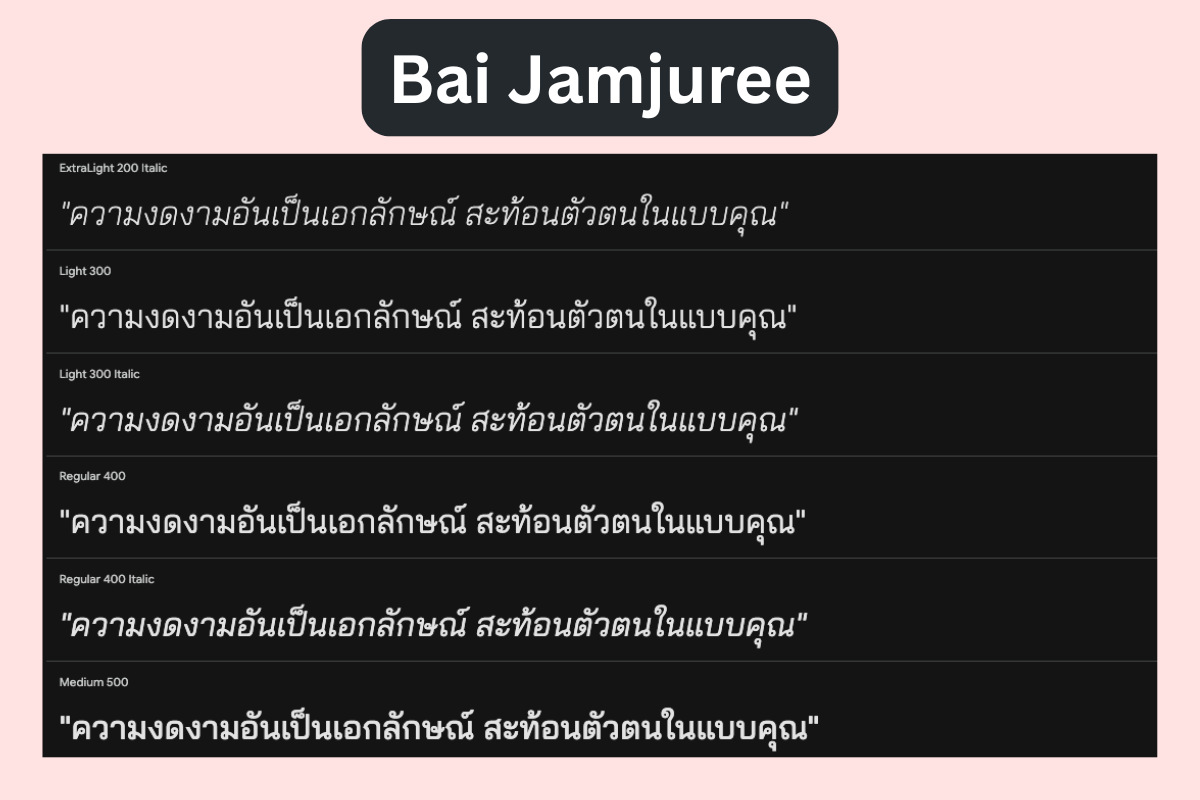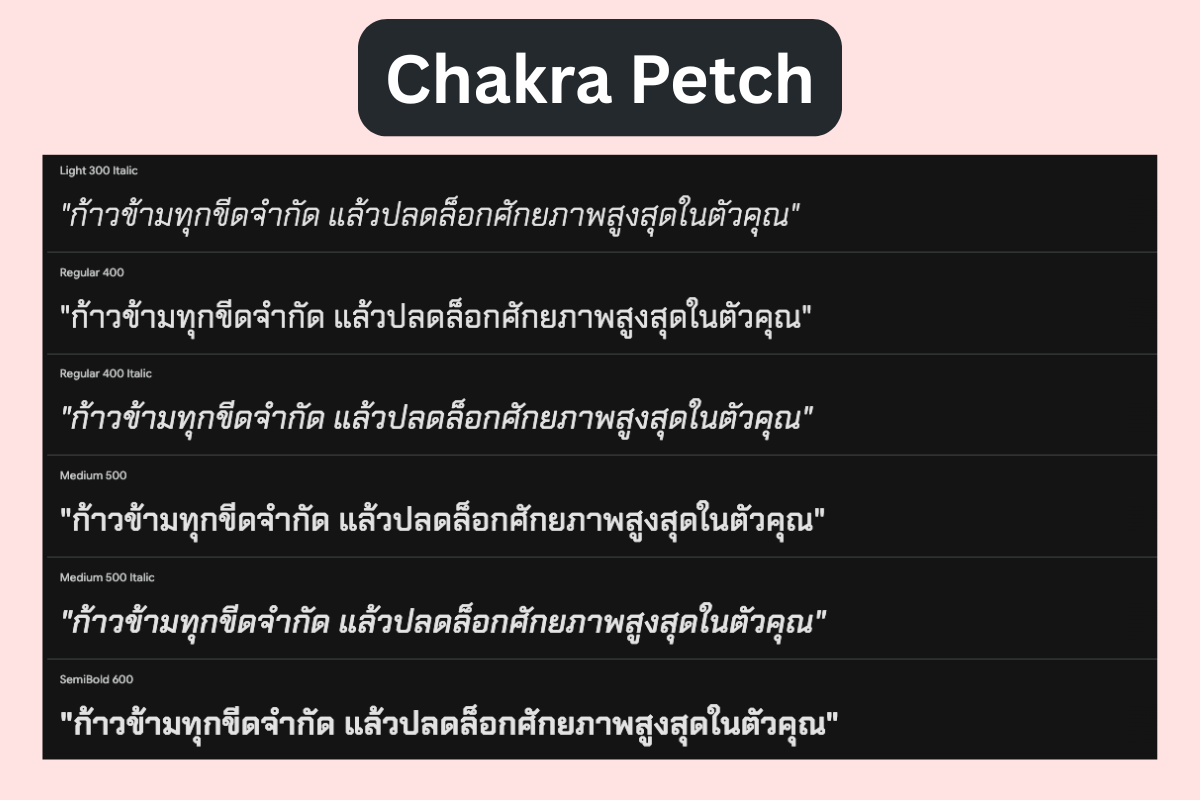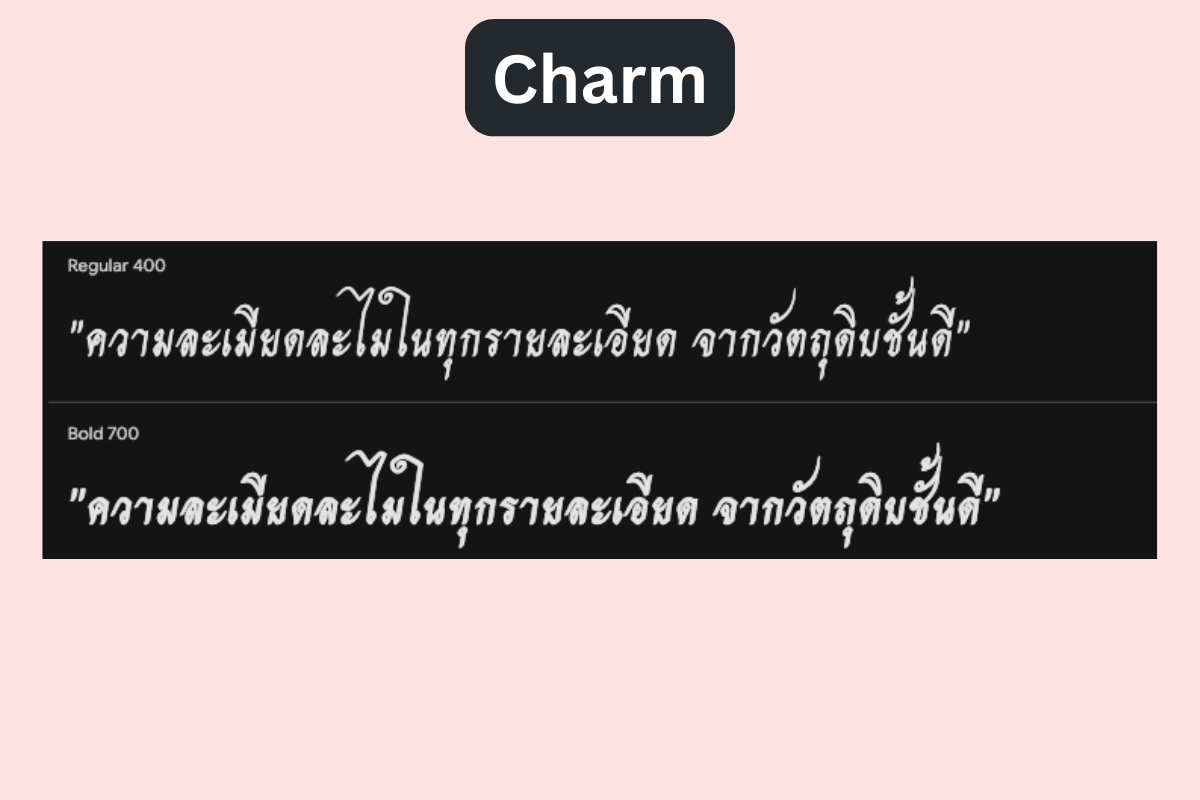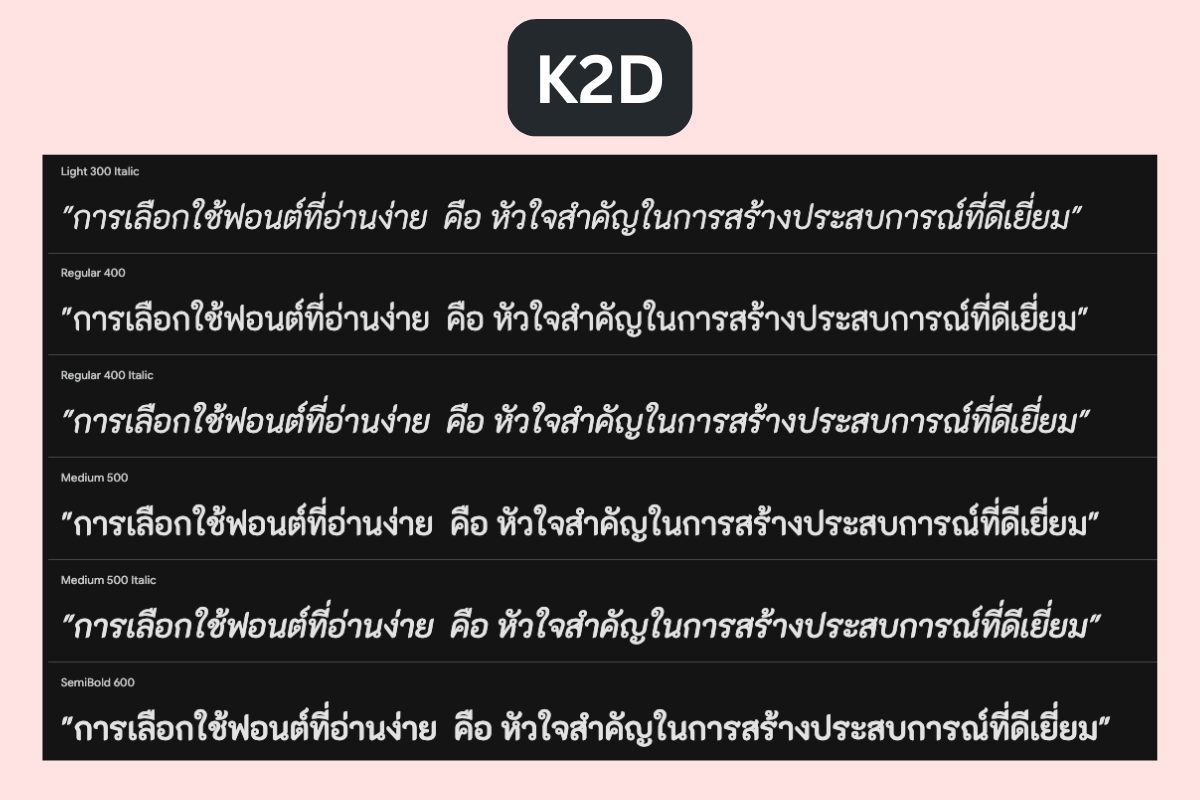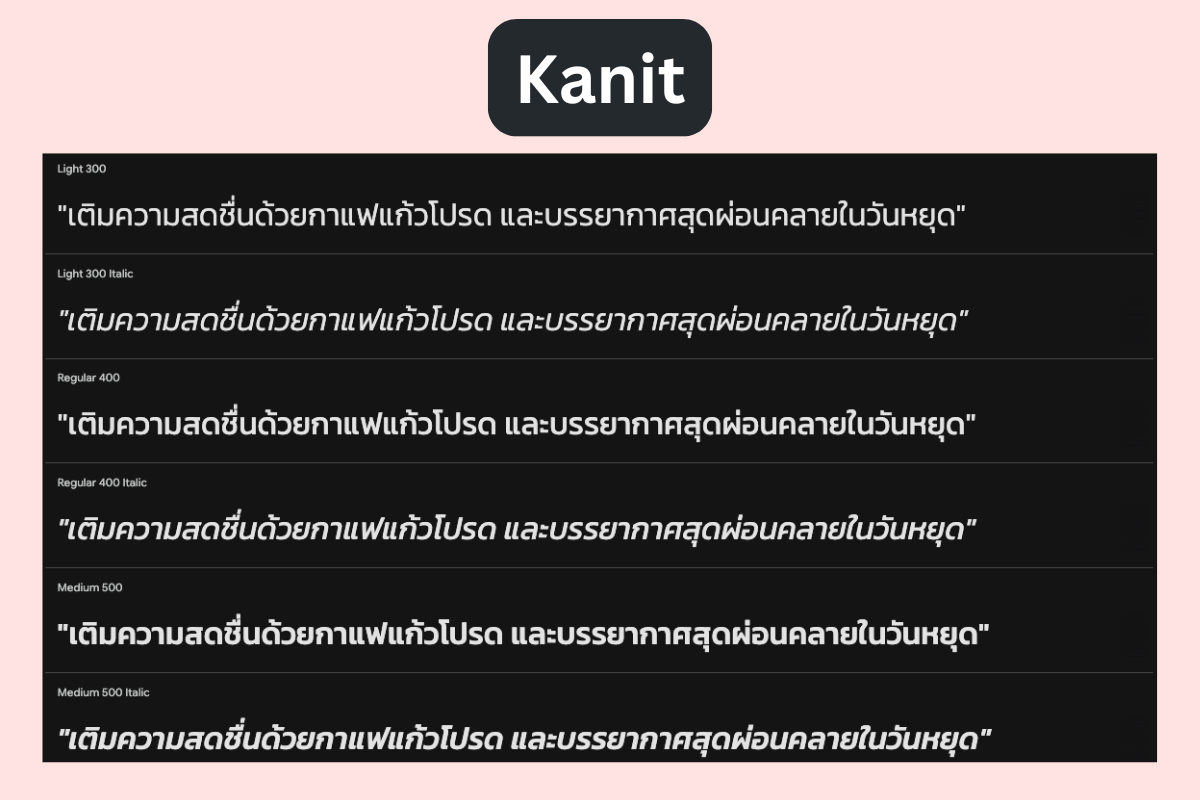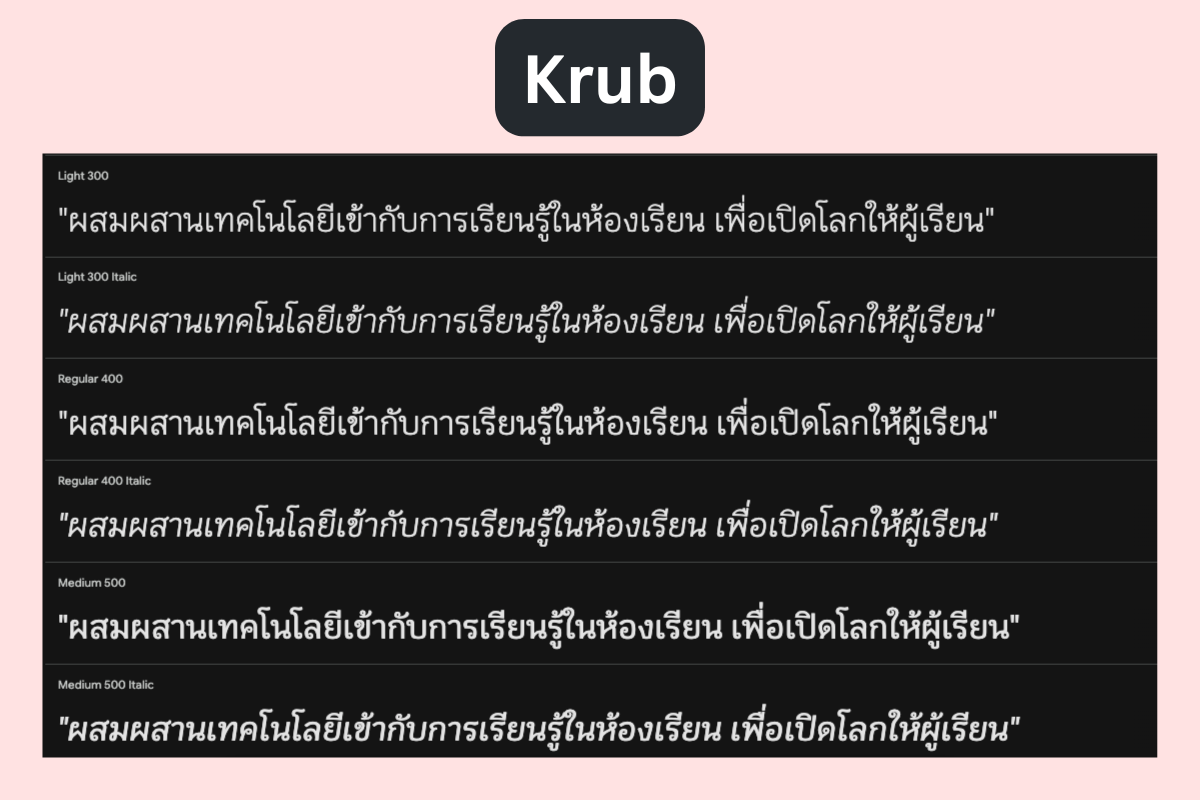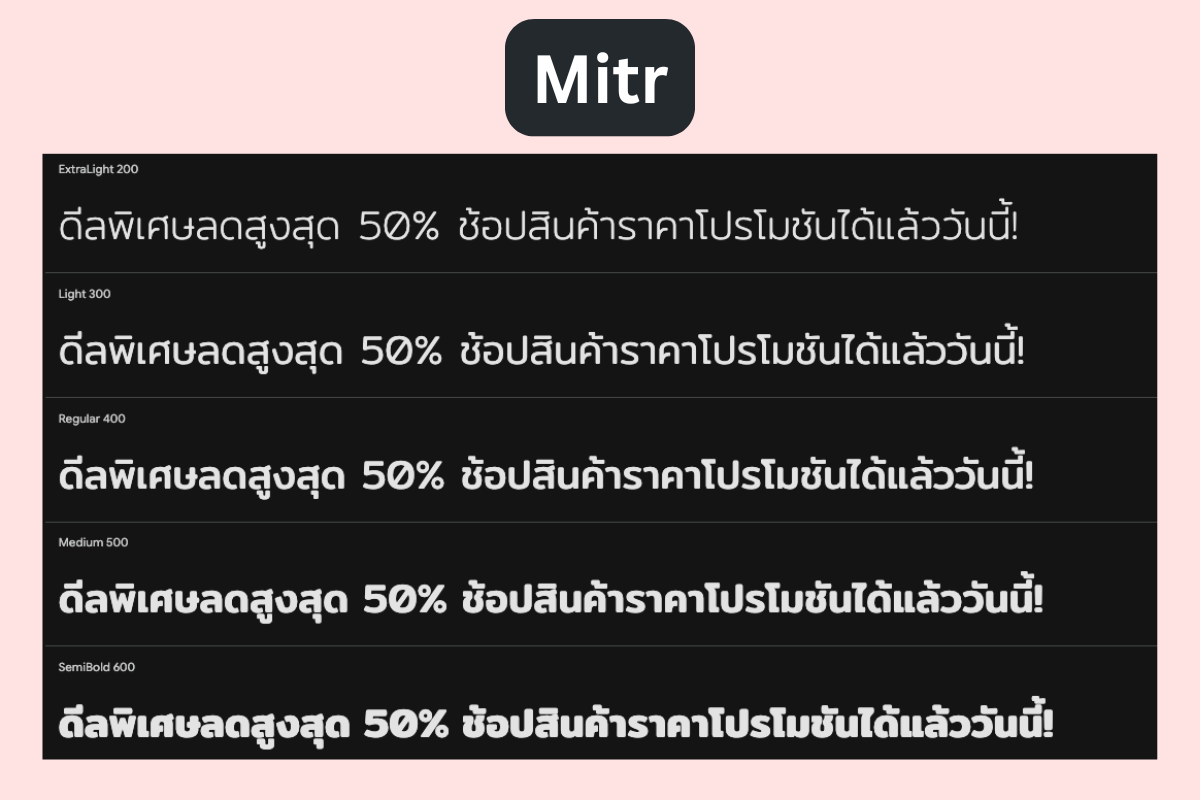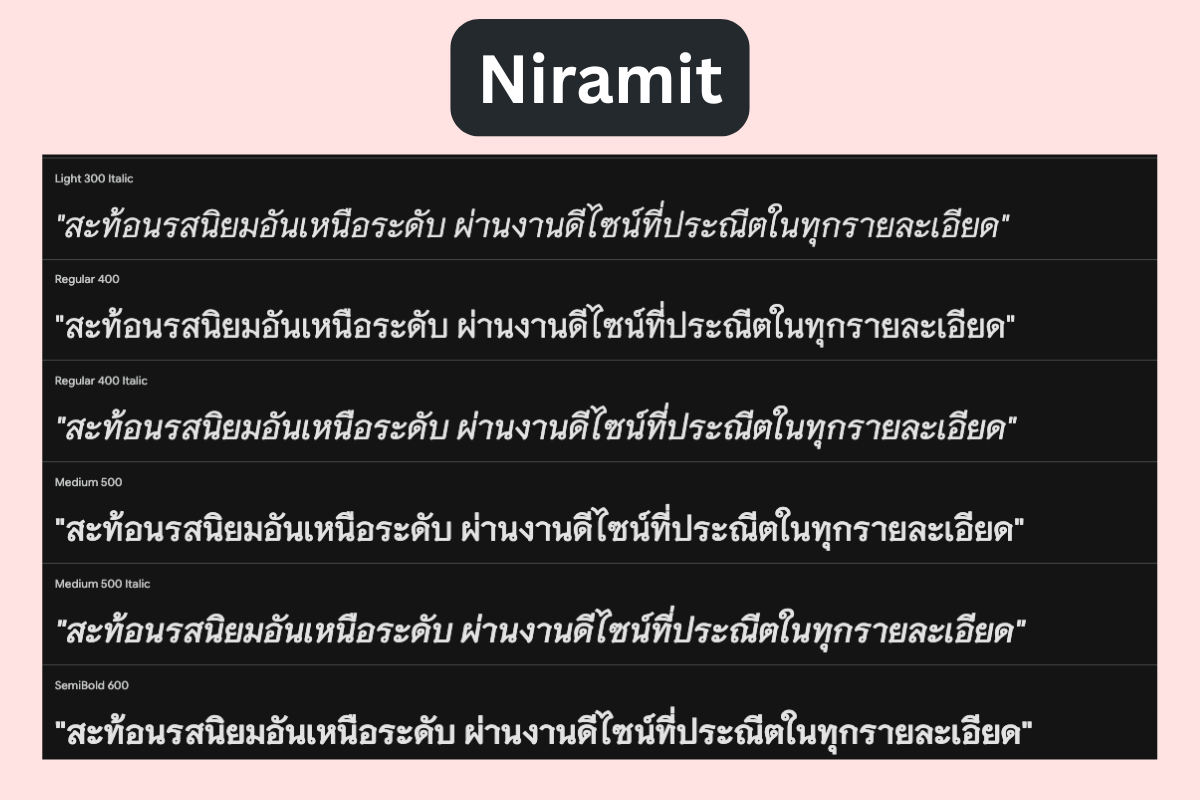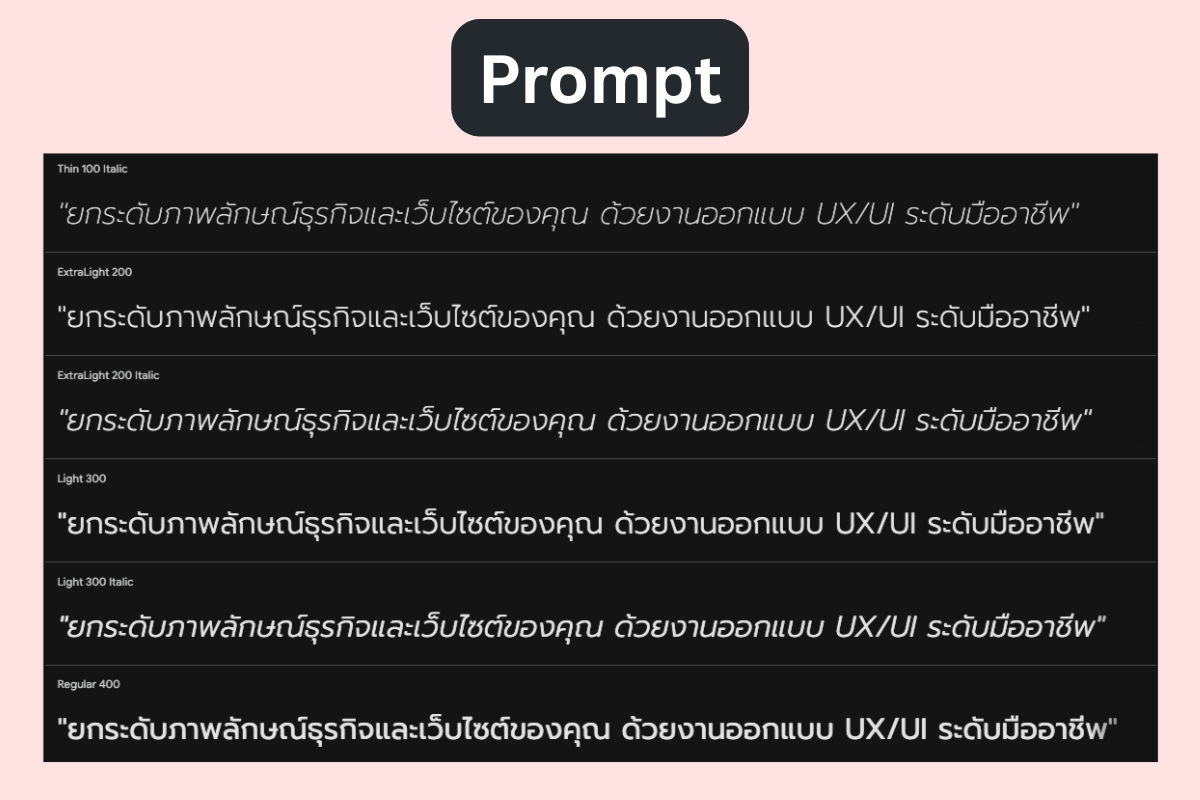
10 Thai Fonts ฟรีที่แนะนำ
ปี 2026
1. Prompt (พร้อมท์)
ฟอนต์ไทยสไตล์โมเดิร์นยอดฮิตอันดับต้น ๆ ของวงการดีไซน์ โครงสร้างอักษรมีความเป็นสากล โปร่งกว้าง และสะอาดตา
ช่วยเพิ่มภาพลักษณ์ความทันสมัย และสร้างความเป็นมืออาชีพให้กับแบรนด์ได้อย่างสมบูรณ์แบบ
• สไตล์: Sans-serif (ไม่มีหัว) | น้ำหนัก: 9 ตัว
(Thin ถึง Black)
• เหมาะกับอะไร: หัวข้อเว็บไซต์ (H1/H2), งาน UI Design,
โพสต์โซเชียลมีเดีย ที่ต้องการลุคโมเดิร์น
และเป็นทางการในเวลาเดียวกัน
• ไม่เหมาะกับอะไร: ย่อหน้าเนื้อหายาว ๆ ที่มีขนาดตัวอักษรเล็กมาก เพราะอาจอ่านยากกว่าฟอนต์มีหัว
2. Sarabun (สารบัญ)
ฟอนต์มาตรฐานระดับประเทศ ที่ออกแบบมาเพื่อการอ่านเนื้อหาปริมาณมากโดยเฉพาะ มีโครงสร้างตัวอักษรแบบมีหัวที่ชัดเจน
เป็นระเบียบ เรียบง่าย และสบายตา ทำให้เป็นตัวเลือกหลักสำหรับงานที่เน้นความน่าเชื่อถือ
• สไตล์: Serif (มีหัวแบบมาตรฐาน) | น้ำหนัก: 8 ตัว
(Thin ถึง Bold)
• เหมาะกับอะไร: ย่อหน้าเนื้อหาบทความ (Body Text), เอกสารทางการขององค์กร,
เว็บไซต์ข่าว และรายงานประจำปี
• ไม่เหมาะกับอะไร: งานที่ต้องการความโฉบเฉี่ยว
ทันสมัยมาก ๆ หรือแบรนด์สายวัยรุ่น
3. Kanit (คณิต)
ฟอนต์ไม่มีหัวที่มีจุดเด่นด้านความทรงพลังและความกว้าง
ของสัดส่วนตัวหนังสือ ให้ความรู้สึกโฉบเฉี่ยว ตื่นตัว และดึงดูดสายตาได้ทันที
จึงมักถูกนำไปใช้ในงานที่ต้องการสร้างความสะดุดตาเป็นพิเศษ
• สไตล์: Sans-serif (ไม่มีหัว โครงสร้างกว้าง ลุคสปอร์ต) | น้ำหนัก: 9 ตัว
• เหมาะกับอะไร: ป้ายโปรโมชัน, ข้อความพาดหัว
ที่เน้นความโดดเด่นสะดุดตา, แบรนด์สายฟิตเนส หรือสินค้าไอที
• ไม่เหมาะกับอะไร: การนำไปใช้เป็นตัวหนังสืออ่านยาวๆ
หลายพารากราฟ
4. K2D (เคทูดี)
ฟอนต์แนวโมเดิร์น Sans-serif ที่ผสมผสานความโค้งมน
เข้ากับเส้นสายที่สะอาดตา ให้ภาพลักษณ์ที่เป็นมิตร
เข้าถึงง่าย แต่ยังคงความเรียบร้อย มักถูกเลือกใช้ในธุรกิจยุคใหม่
ที่ต้องการสร้างบรรยากาศผ่อนคลาย และทันสมัย
• สไตล์: Sans-serif (ไม่มีหัว สไตล์โมเดิร์นโค้งมน) |
น้ำหนัก: 6 ตัว
• เหมาะกับอะไร: เว็บไซต์เทคโนโลยี, สตาร์ตอัป,
หน้าขายสินค้า (Landing Page),
โพสต์โฆษณาบนโซเชียลมีเดียที่ต้องการความรู้สึกเป็นมิตร
• ไม่เหมาะกับอะไร: งานเอกสารทางการมากๆ
เช่น สัญญากฎหมาย หรือหนังสือราชการ
5. Chakra Petch (จักรเพชร)
ฟอนต์ทรงเหลี่ยมที่มีเอกลักษณ์โดดเด่นสไตล์เทคโนโลยี โครงสร้างตัวอักษรเน้นมุมตัดและเส้นตรงที่แข็งแกร่ง
ให้ความรู้สึกเหมือนโลกอนาคต เครื่องจักร นวัตกรรม และไซเบอร์ได้อย่างชัดเจน
• สไตล์: Square Sans-serif (ไม่มีหัว ทรงเหลี่ยมเทคโนโลยี) | น้ำหนัก: 5 ตัว
• License: SIL Open Font License 1.1
• เหมาะกับอะไร: เว็บไซต์เกม, ธุรกิจยานยนต์, นวัตกรรม AI, งานออกแบบสไตล์ไซเบอร์พังก์
• ไม่เหมาะกับอะไร: ธุรกิจบริการสุขภาพ, แบรนด์เด็ก
หรือสินค้าสปา
6. Niramit (นิรมิต)
ฟอนต์แบบมีหัวที่มีกลิ่นอายความเป็นไทยอย่างชัดเจน
เส้นสายมีความงดงาม โปร่งกว้าง เรียบร้อย และคลาสสิก
ให้ความรู้สึกสงบนิ่ง น่าเชื่อถือ และสะท้อนภาพลักษณ์
ความสง่างามแบบไทยได้อย่างลงตัว
• สไตล์: Modern Serif (มีหัวสไตล์โมเดิร์น) |
น้ำหนัก: 6 ตัว
• License: SIL Open Font License 1.1
• เหมาะกับอะไร: หนังสือ, นิตยสารเชิงวัฒนธรรม,
สื่อประชาสัมพันธ์องค์กรไทย,
บรรจุภัณฑ์สินค้าไทยพรีเมียม หรือสถาบันการศึกษา
• ไม่เหมาะกับอะไร: สื่อสายเทคโนโลยี, สตาร์ตอัป, สื่อวัยรุ่น
หรือเว็บไซต์ที่ต้องการความฉูดฉาด
7. Mitr (มิตร)
ฟอนต์กึ่งมีหัวที่ออกแบบมาให้อ่านง่าย สบายตา
และดูเป็นมิตรตามชื่อ มีความสมดุลระหว่างความทันสมัย
กับโครงสร้างแบบดั้งเดิม ทำให้เข้าถึงคนได้ทุกกลุ่มวัย
โดยไม่ดูเป็นทางการจนเกินไป
• สไตล์: Semi-sans-serif (มีหัวมินิมอล) | น้ำหนัก: 6 ตัว
• License: SIL Open Font License 1.1
• เหมาะกับอะไร: แอปพลิเคชันการศึกษา, เว็บไซต์สถาบันติวเตอร์, เนื้อหาอินโฟกราฟิก
• ไม่เหมาะกับอะไร: แบรนด์ที่ต้องการภาพลักษณ์ดุดัน
หรือหรูหราระดับไฮเอนด์
• ดาวน์โหลดทางการ: Google Fonts – Mitr
8. Krub (ครับ)
ฟอนต์ Display สไตล์ไทยร่วมสมัยที่มีเอกลักษณ์เฉพาะตัวสูงมาก ด้วยดีไซน์หัวอักษรแบบม้วนขมวด
และเส้นสายคดเคี้ยวสลับซับซ้อน มอบอารมณ์ศิลป์
และความโดดเด่นที่ไม่ซ้ำใครให้กับงานดีไซน์
Thai-Fonts-Krub
• สไตล์: Serif / Display (หัวม้วนขมวด มีเอกลักษณ์เฉพาะตัวสูง) | น้ำหนัก: 6 ตัว
• License: SIL Open Font License 1.1
• เหมาะกับอะไร: งานออกแบบพาดหัวสั้นๆ (Headline),
งานการ์ดอวยพร, ป้ายร้าน, โลโก้
หรือสื่อที่ต้องการลุคแบบงานคราฟต์/อาร์ต
• ไม่เหมาะกับอะไร: ตัวหนังสืออ่านยาวๆ (Body Text),
งานเอกสารทางการ, งาน UI
หรือหน้าเว็บที่ต้องการความคลีน สบายตา
• ดาวน์โหลดทางการ: Google Fonts – Krub
9. Charm (ชาร์ม)
ฟอนต์สไตล์ Script ลายมือหวัดตัวเขียนอ่อนช้อย พริ้วไหวสวยงาม ถ่ายทอดความรู้สึกอ่อนโยน ละมุนละไม และโรแมนติก
ช่วยเติมเสน่ห์ และความพรีเมียมสไตล์งานทำมือให้กับชิ้นงาน
Thai-Fonts-Chram
• สไตล์: Script (ลายมือหวัดอ่อนช้อย) | น้ำหนัก: 2 ตัว
• License: SIL Open Font License 1.1
• เหมาะกับอะไร: การ์ดอวยพร, โลโก้ร้านขนม,
บรรจุภัณฑ์สินค้าออร์แกนิก
• ไม่เหมาะกับอะไร: การนำไปใช้เป็นฟอนต์หลักของเว็บไซต์ หรือเนื้อหาย่อย
• ดาวน์โหลดทางการ: Google Fonts – Charm
10. Bai Jamjuree (ไทรจามจุรี)
ฟอนต์กึ่งทรงเหลี่ยมมีหัวที่ถูกพัฒนามาเพื่อเน้นการจัดเรียงข้อมูลที่มีความซับซ้อนให้ดูเป็นระเบียบ อ่านง่ายสบายตา
ให้ลุคที่เป็นระบบ มีโครงสร้างชัดเจน และทรงพลัง
Thai-Fonts-Bai-Jamjuree
• สไตล์: Semi-serif (ทรงกึ่งเหลี่ยมมีหัว) | น้ำหนัก: 6 ตัว
• License: SIL Open Font License 1.1
• เหมาะกับอะไร: หน้าแสดงผลตารางข้อมูล, ระบบบริหารจัดการหลังบ้าน (ERP/CRM), แอปการเงิน
• ไม่เหมาะกับอะไร: งานสื่อสิ่งพิมพ์การ์ดแต่งงาน
หรือสินค้าแนววินเทจ
• ดาวน์โหลดทางการ: Google Fonts – Bai Jamjuree
License ของ Thai Fonts ฟรี: OFL, Apache 2.0 และ Free for Personal Use ต่างกันอย่างไร?
ปัญหาส่วนใหญ่ที่ทำให้ธุรกิจถูกฟ้องร้องเรื่องลิขสิทธิ์ฟอนต์
มาจากความเข้าใจผิด ว่า
“ดาวน์โหลดฟรี = นำไปใช้ทำอะไรก็ได้”
ซึ่งในความเป็นจริง สัญญาอนุญาตแบ่งออกเป็น 3 ประเภทหลัก ๆ :
SIL Open Font License (OFL)
เป็น License ยอดนิยมบน Google Fonts ที่เสรีที่สุด
เพราะเจ้าของฟอนต์หลาย ๆ เจ้า อนุญาตให้คุณนำฟอนต์ไทยไป
ทั้งใช้ในงานส่วนตัว และงานเชิงพาณิชย์ (Commercial Use)
ได้ฟรีแบบ 100% ทั้งบนสิ่งพิมพ์ เว็บไซต์ แอปพลิเคชัน
หรือสื่อโฆษณา รวมถึงสามารถนำไปฝัง (Embed) ในโค้ดเว็บได้
โดยไม่ต้องเสียค่าใช้จ่าย
Apache License 2.0
มีความคล้ายคลึงกับ OFL พอสมควร
เนื่องจากเปิดให้ใช้นำไปประกอบธุรกิจได้ฟรี
แต่ฟอนต์บางประเภทก็จะมีข้อกำหนดเพิ่มเติม
ในฝั่งนักพัฒนาซอฟต์แวร์ เช่น หากมีการแก้ไขตัวโค้ดฟอนต์
เพื่อแจกจ่ายต่อ ต้องมีการแนบเอกสารแจ้งสิทธิ์
และเครดิตของต้นฉบับไว้ในระบบด้วย
Thai Fonts ที่ฟรีเฉพาะงานส่วนตัว — วิธีเช็กก่อนใช้ในงานลูกค้า
ฟอนต์ตามเว็บแจกฟอนต์ทั่วไปจำนวนมาก มีการระบุเงื่อนนไขการใช้งานว่าเป็นฟอนต์สำหรับ Personal Use Only
แปลว่าคุณสามารถใช้ทำการบ้านทำพอร์ตโฟลิโอส่งครู
หรือทำคอนเทนต์ที่ไม่ได้ถูกนำไปยิงโฆษณาได้ฟรี
แต่ห้ามนำไปใช้กับงานที่มีการจ้างวาน เช่น ทำเพจร้านค้า
ทำแบนเนอร์สินค้าให้ลูกค้า หรือแปะบนหน้าเว็บขายของ
เพราะถ้าหากนำไปใช้ จะถือว่าละเมิดลิขสิทธิ์ทันที
Checklist 4 ข้อ ก่อนใช้ Thai Fonts ฟรีในงานเชิงพาณิชย์
1. อ่านไฟล์ Readme / License.txt ที่ติดมากับโฟลเดอร์ Zip เสมอ
2. จับภาพหน้าจอ (Screenshot) หน้าเว็บที่ดาวน์โหลด
ซึ่งระบุข้อความ “Free for Commercial Use”
เก็บไว้เป็นหลักฐาน
3. ตรวจสอบว่าเป็นการดึงผ่านระบบที่ถูกต้อง
เช่น การเรียกใช้ Google Fonts API
หรือดาวน์โหลดจากเว็บผู้สร้างโดยตรง
4. หากเป็นฟอนต์ที่มีสัญลักษณ์ ® หรือ ™ ให้ตรวจสอบ
กับสัญญาขายฟอนต์ของผู้ผลิต
ว่ามีขอบเขตการใช้งานอย่างไร
วิธีจับคู่ Thai Fonts (Font Pairing)
ให้ดูเป็นมืออาชีพ
หลักการสำคัญในการเลือกฟอนต์ไทยสำหรับทำเว็บไซต์ และกราฟิก คือ “อย่าใช้เกิน 2–3 ฟอนต์ในหน้าเดียวกัน”
เพื่อรักษาความเรียบร้อย (Consistency)
นี่คือสูตรจับคู่ที่ทีม UX/UI ของเรานิยมใช้:
• สูตรโมเดลธุรกิจ (Business/Corporate):
ใช้
Prompt เป็นหัวข้อ (H1/H2) เพื่อสร้างความโดดเด่น
+ ใช้
Sarabun เป็นเนื้อหา (Body) เพื่อให้อ่านง่าย
• สูตรเทคโนโลยี/สตาร์ตอัป (Tech/Startup):
ใช้
K2D เป็นหัวข้อ + ใช้ Bai Jamjuree เป็นเนื้อหา
สร้างลุคล้ำสมัย เป็นมิตร และอ่านเป็นระบบ
• สูตรแฟชั่น/คลินิกความงาม (Beauty/Fashion):
ใช้
Niramit เป็นหัวข้อ + ใช้ Mitr เป็นเนื้อหา
ช่วยให้ภาพรวมดูพรีเมียม ร่วมสมัย และเข้าถึงง่าย
วิธีติดตั้ง Thai Fonts: Windows, macOS, Canva, Figma และ Google Docs
ขั้นตอนการติดตั้งฟอนต์บน Windows
1. แตกไฟล์ .zip ที่ดาวน์โหลดฟอนต์มา
2. คัดลอกไฟล์ฟอนต์สกุล .ttf หรือ .otf
3. ไปที่ C:\Windows\Fonts แล้วกดวาง (Paste)
หรือคลิกขวาที่ไฟล์ฟอนต์
แล้วเลือก
Install for all users >>  ฟอนต์จะถูกติดตั้ง
ลงในระบบ และสามารถใช้งานได้ทันที
ในโปรแกรมต่าง ๆ เช่น Microsoft Word
หรือ
Adobe Photoshop
ขั้นตอนการติดตั้งฟอนต์บน macOS
1. ดับเบิลคลิกที่ไฟล์ฟอนต์ .ttf หรือ .otf
2. หน้าต่าง Font Book จะเด้งขึ้นมา ให้กดปุ่ม Install Font >> ฟอนต์จะถูกติดตั้งในแอปพลิเคชัน Font Book และสามารถใช้งานได้ในโปรแกรมต่าง ๆ ที่รองรับ
วิธีนำ Thai Fonts ไปใช้ใน Canva
• สำหรับผู้ใช้ Canva Pro: ไปที่ Brand Hub > Brand Kits > เลือก Upload a font
แล้วแนบไฟล์
.ttf
(ต้องเช็ก License ว่ารองรับ Commercial Use ก่อนอัปโหลด)
• สำหรับผู้ใช้ Canva Free: สามารถค้นหาฟอนต์
อย่าง Prompt, Sarabun, Kanit ได้ในช่องค้นหาฟอนต์
ของระบบได้ทันที เพราะ Canva นำคลัง Google Fonts
มาลงไว้ให้อยู่แล้ว
วิธีนำ Thai Fonts ไปใช้ใน Figma
• สำหรับ Figma Desktop App: สามารถเรียกใช้ฟอนต์
ที่ติดตั้งอยู่ในเครื่องคอมพิวเตอร์ได้ทันที
• สำหรับ Figma Web Browser: ต้องดาวน์โหลดโปรแกรม Figma Font Installer
มาติดตั้งในเครื่องก่อน ระบบบนเว็บจึงจะมองเห็นฟอนต์ในเครื่อง
วิธีนำ Thai Fonts ไปใช้ใน Google Docs
• คลิกที่ช่องเลือกฟอนต์ > เลือก More fonts
> พิมพ์ชื่อฟอนต์ภาษาไทย เช่น “Prompt” หรือ “Sarabun”
แล้วกดตกลง ฟอนต์จะถูกเพิ่มเข้าในระบบ Google Docs ทันที
แหล่งดาวน์โหลด Thai Fonts ฟรีที่เชื่อถือได้ (และข้อควรระวัง)
• Google Fonts: แหล่งที่ปลอดภัยที่สุดในโลก
ทุกฟอนต์เป็น Open Source ใช้เชิงพาณิชย์ได้ฟรี
• f0nt.com: เว็บไซต์ชุมชนฟอนต์ไทยที่ใหญ่ที่สุด
มีทั้งฟอนต์ฟรี 100% และแบบที่เปิดให้ใช้ฟรีแค่ส่วนตัว
ข้อควรระวัง: ควรอ่านรายละเอียดเงื่อนไขของผู้สร้าง
ที่เขียนไว้ใต้โพสต์แจกฟอนต์ทุกครั้งก่อนโหลด
• ข้อควรระวังเว็บละเมิดลิขสิทธิ์: หลีกเลี่ยงการดาวน์โหลดฟอนต์แจกฟรีจากกลุ่ม Facebook หรือเว็บฝากไฟล์
ที่ไม่ระบุผู้สร้าง เพราะมักเป็นการนำฟอนต์มีลิขสิทธิ์ของค่ายดังมาแจกแบบผิดกฎหมาย
คำถามที่พบบ่อย
เกี่ยวกับ Thai Fonts (FAQ)
Q: ฟอนต์ฟรีจาก Google Fonts นำไปใช้ทำโลโก้เครื่องหมายการค้า (Trademark) ได้ไหม?
A: ได้ เพราะสัญญาอนุญาตแบบ SIL Open Font License (OFL) อนุญาตให้นำฟอนต์ไปใช้แปลงเป็นเวกเตอร์
เพื่อทำโลโก้สินค้า และจดทะเบียนเครื่องหมายการค้า
ได้โดยไม่ต้องจ่ายค่าลิขสิทธิ์เพิ่ม
Q: หากนำฟอนต์ฟรีไปใช้ทำเว็บให้ลูกค้า
จะถูกคิดค่าฝั่งฟอนต์
(Web Font License) ไหม?
A: หากใช้ฟอนต์ที่เป็น OFL หรือดึงผ่าน Google Fonts API จะไม่มีการเก็บค่าบริการย่อยใดๆ เพิ่มเติม สามารถใช้งาน
บนเว็บไซต์ที่มีผู้เข้าชมหลักล้านคนได้ฟรี
สรุปเกี่ยวกับ Thai Fonts ฟรีสำหรับธุรกิจ
การเลือกใช้ ฟอนต์ไทยฟรี สำหรับงานเชิงพาณิชย์ไม่ใช่เรื่องยาก เพียงแค่คุณเลือกดาวน์โหลดจากแหล่งที่น่าเชื่อถือ
อย่าง Google Fonts หรือเช็กสัญญาอนุญาต
ให้เป็นประเภท
OFL เท่านี้คุณก็จะได้งานดีไซน์ที่สวยงาม เป็นมืออาชีพ
และปลอดภัยจากปัญหาละเมิดลิขสิทธิ์ย้อนหลังแล้วครับ
ต้องการออกแบบเว็บไซต์องค์กรที่คุมโทนแบรนด์
ใช้ฟอนต์ถูกต้องตามหลัก UX/UI และโหลดไวติดสปีด?
สามารถปรึกษาผู้เชี่ยวชาญ
ของ Yes Web Design Studioได้เลย
เพราะเราเป็นบริษัทเว็บดีไซน์แนวหน้าในไทย
ที่รับทำเว็บไซต์แบบครบวงจร
รวมถึงบริการรับทำ SEO และการตลาดออนไลน์
เพื่อช่วยให้ธุรกิจของคุณเติบโตได้อย่างมีประสิทธิภาพ
Yes Web Design Studio
Tel. : 096-879-5445
LINE : @yeswebdesign
E-mail :
Address : ชั้น 17 อาคารวิทยกิตติ์ ถนนพญาไท วังใหม่ ปทุมวัน กรุงเทพมหานคร 10330 (สถานี BTS สยาม)
Thaifonts.net 100+ ⚠️ บางแบบ ❌ หลากสไตล์ ค้นหาง่าย